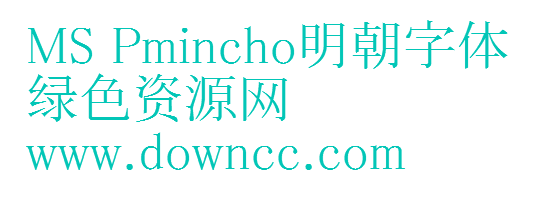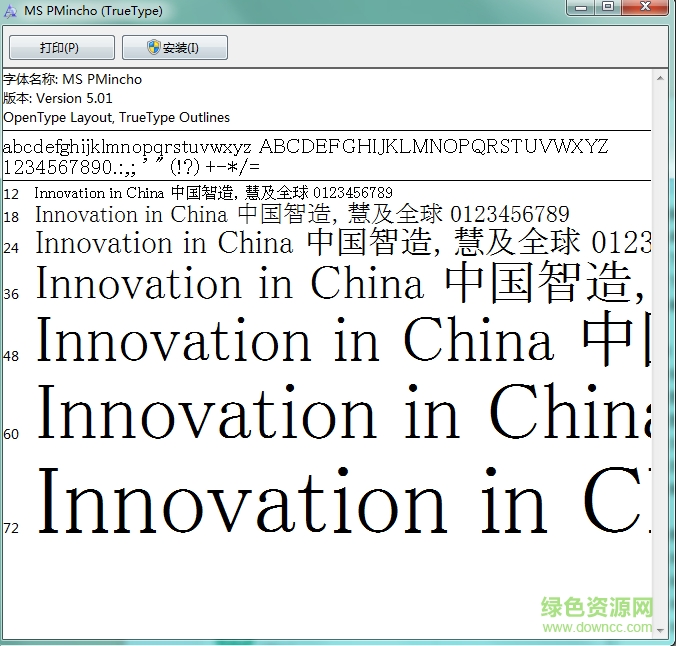
ms pmincho(明朝體)
ms pmincho是一款纖細(xì)的明朝字體,與MS Mincho字體類似,部分系統(tǒng)自帶該字體,如您需要可以來(lái)綠色資源網(wǎng)免費(fèi)下載使用哦!
ms pmincho是什么字體
ms pmincho即 MS P明朝 標(biāo)準(zhǔn),是一種日文字體,字跡娟秀簡(jiǎn)潔,支持繁簡(jiǎn)體輸入,字庫(kù)較全,可廣泛運(yùn)用于名片設(shè)計(jì)、品牌商標(biāo)、廣告創(chuàng)意、藝術(shù)創(chuàng)作等諸多領(lǐng)域!
ms pmincho介紹
明朝體作為電腦字體的英文名稱是“Ms Mincho”和“Ms PMincho”。一般電腦操作系統(tǒng)自帶的字庫(kù)里面包含該字體,若沒(méi)有,可以去綠色資源網(wǎng)進(jìn)行下載。特別是在處理日語(yǔ)文檔的時(shí)候需要在word辦公軟件中,將字體設(shè)置為“Ms Mincho”。
明朝體說(shuō)明
廣義的明朝體指的是日本、韓國(guó)等對(duì)宋體字的叫法。狹義則僅指一種日文電腦字體。
元明時(shí)期,戲曲小說(shuō)的大量刊行,對(duì)雕版印刷技術(shù)有了新的要求。為了提高效率,雕版師傅們不約而同地開(kāi)始對(duì)字體進(jìn)行改良,最終形成了一種橫細(xì)豎粗的,專為印刷雕版使用的字體,也就是宋體字。宋體字在明朝時(shí)傳入日本,因而日本稱之為“明體”或“明朝體”。
在電腦漢字字體設(shè)計(jì)的最初,日本率先設(shè)計(jì)了明朝體,后來(lái)傳入韓國(guó)、中國(guó)臺(tái)灣,所以兩地也有明朝體的叫法。時(shí)至今日,由于中日兩國(guó)文字簡(jiǎn)化方案的不同,兩國(guó)文字已經(jīng)有了很大的不同,明朝體也就徹底成為一種外文字體了。